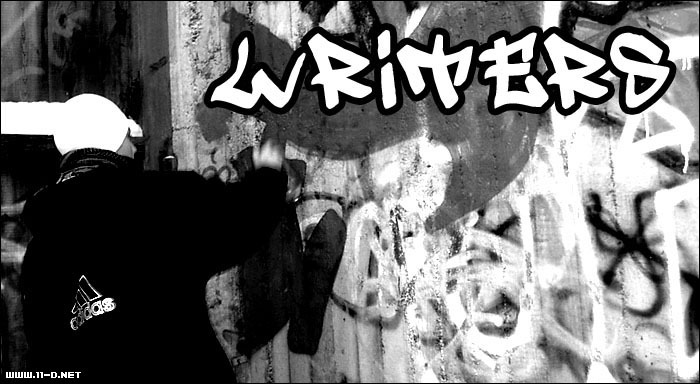
Writers Condensed di Johan Waldenstrom è un font graffiti gratuito che porta con sé l'energia rapida e graffiante del lettering di strada. Le lettere si basano su forme a pennello corpose, giunzioni strette e angoli grezzi, dando al font un ritmo incalzante che trasmette più l'idea di un tag che di un disegno studiato a tavolino.
È ideale per poster, copertine di mixtape, grafiche skate, testate di fanzine, titoli e slogan per merchandising dove l'attitudine grezza del pennarello conta più della rifinitura. Essendo un font gratuito, funziona bene anche per titoli d'impatto, bozzetti di loghi e headline, perché i tratti irregolari e la spaziatura compressa danno vita e dinamismo anche a poche parole.